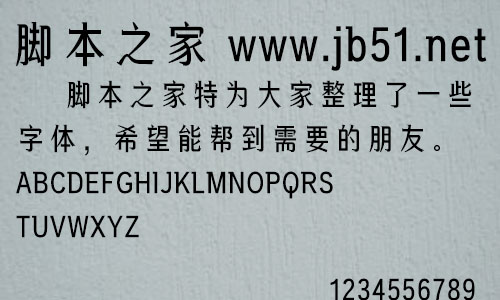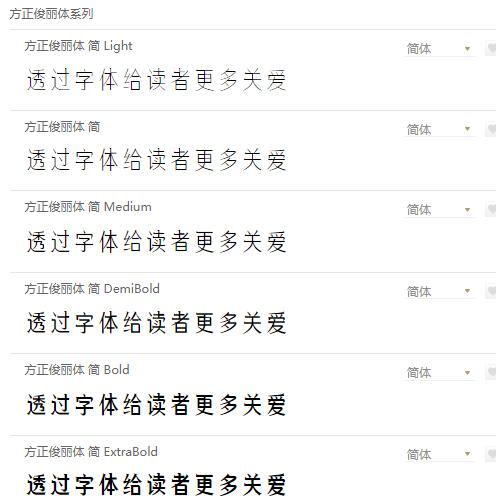
方正俊麗體系列由方正字庫出品的一款不錯的藝術(shù)字體,該系列字體共六款,字形修長,平和工穩(wěn),秀麗雅致,具有很好的視覺感,適合應(yīng)用于藝術(shù)設(shè)計、平面宣傳設(shè)計、網(wǎng)頁設(shè)計,書法等領(lǐng)域。
俊麗體系列是一款個性鮮明的創(chuàng)意字體。字形修長,平和工穩(wěn),秀麗雅致,相較于常見的排版字體更具有識別度??←愺w家族共包含6個字重,可以涵蓋正文和標題的排版使用。適用范圍:商業(yè)廣告、書刊出版、產(chǎn)品包裝等。